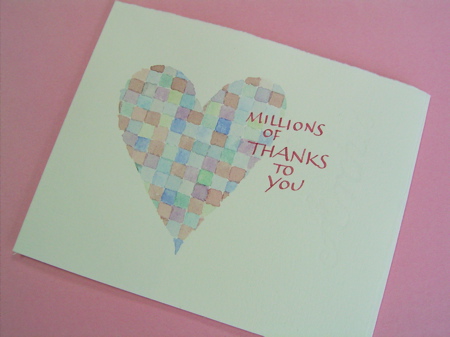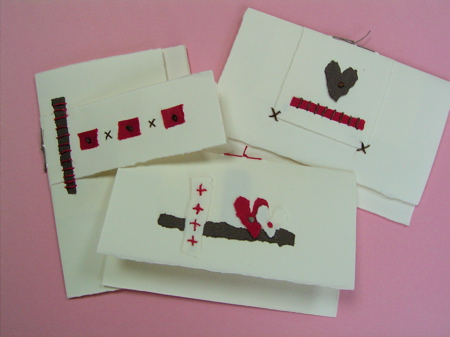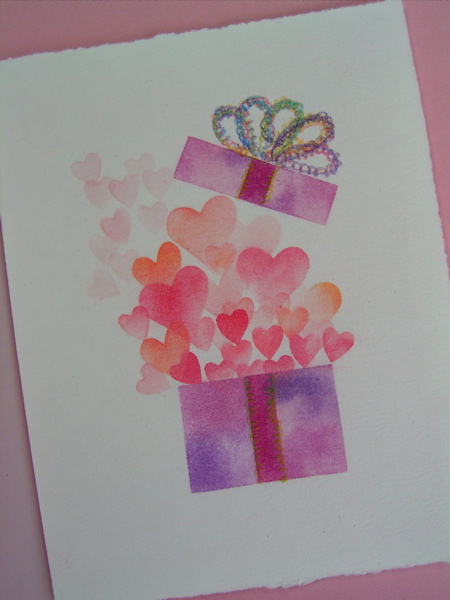
愛しのバレンタイン
この2年間、月に2回の作品の更新などサイトの制作やメンテナンス、その他モジトル運営のアドバイス、アイデアなどなど、言い表せない程非常にお世話になっている方たちへ、毎年恒例、バレンタインデーカードを送っています。
とは言っても、こんなカードでは全然すまされないほど、お世話になっていますので、なにしろ恐縮なのです。人数分を作る上で、きっとちょっとづつデザインが違っていると思いますが、それでも心を込めて作っておりまっす!少しでも喜んで頂けたら嬉しいのですが・・・・。
どれが誰のカードか、わかるかな!?
手作りのカードは、手にする度にほんとドキドキします。
手書きの文字は筆遣いを目で追い、アートの部分はブラシやペンシル、
鋏や針が皆さんの手により活躍する様が目に浮かびます。
これからもどうぞドキドキさせてください。
ただこうしてプレゼントとしていただくと
「自分だけの世界に1点しかない作品だ!」って
いつも以上に感動いたしました。